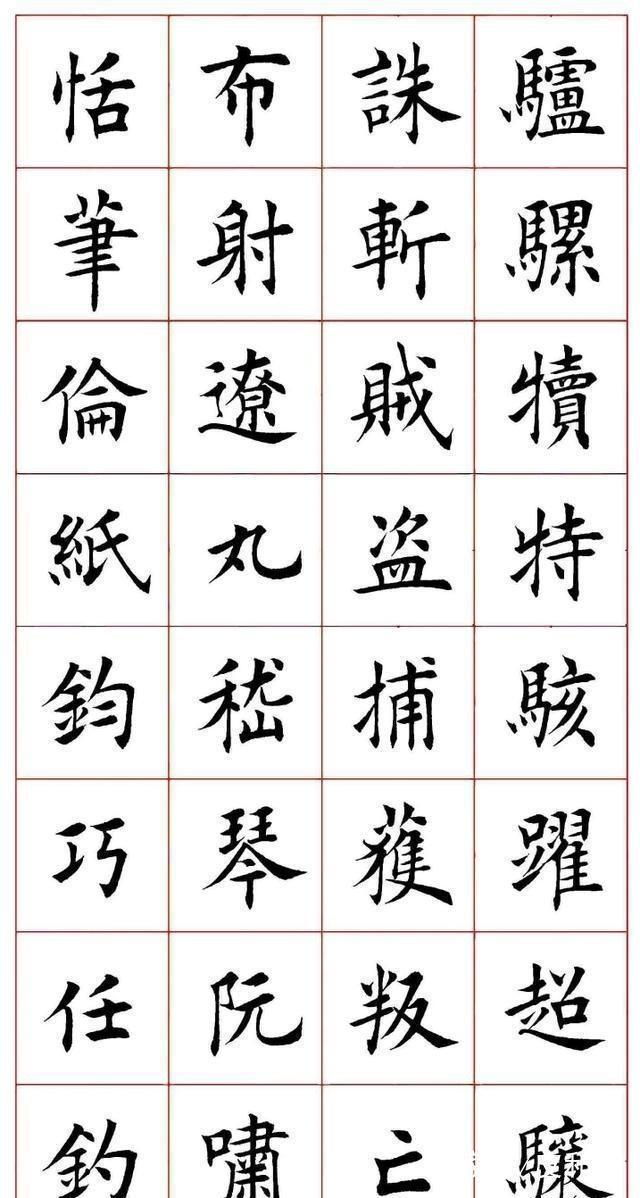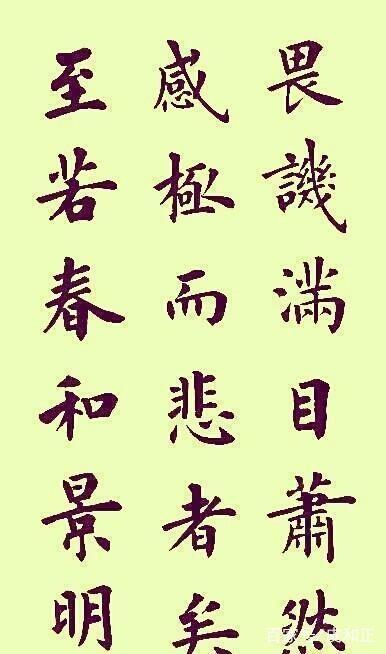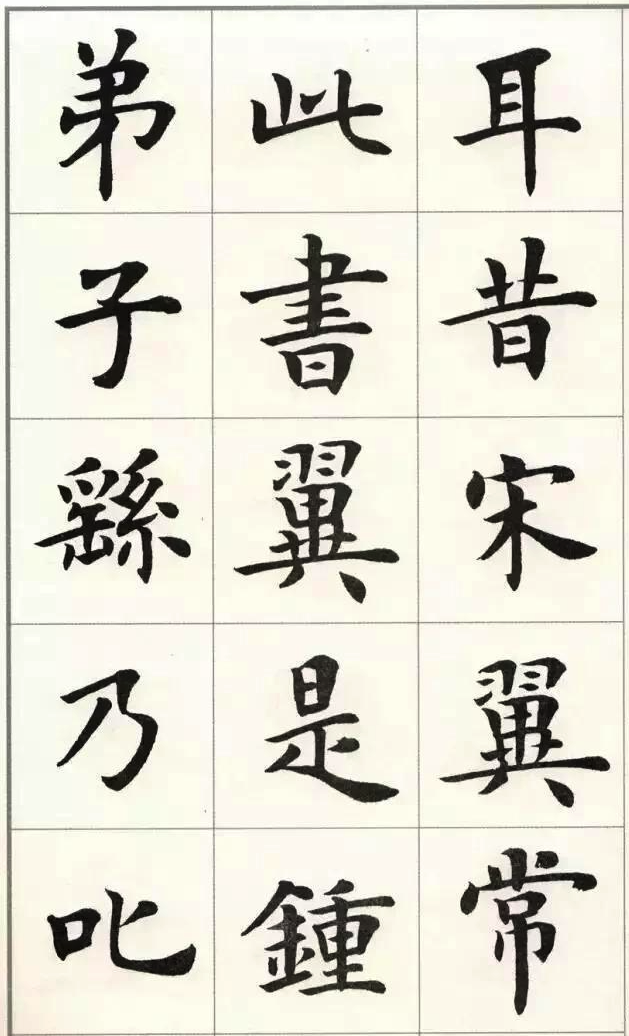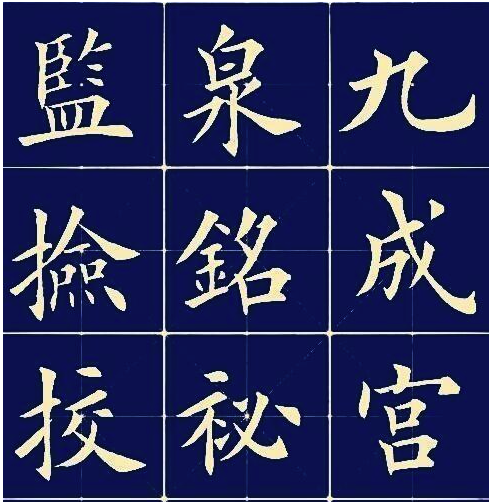
印刷体书法再做成字库是否还有意义?
无论是印刷体书法或者不是印刷体书法,能做成字库让人们做为实用性文字使用,都是一件功在当代,利在千秋的事,其意义是重大的。目前网上已出现启功、田英章、卢中南等人的书法字体。
大家知道,如果自己的字出现在互联网上,或者出现在报纸,杂志,电视等传媒上,那就是专家、学者和大众对你的书法作品的认可,说明你的书法已达到较高的水平,是一件值得自豪且有一定意义的的事情!
并不是谁的字都可以做成字库让国人作为实用性文字使用的。有的人绞尽脑汁想把自己的书法进入字库,可做字库的专家们硬是不理睬他,至于为什么,只有他们自己心里明白。
印刷体书法做成字库后,不仅体现在实用性功能上,并且还承载和传播着中国书法文化,让大众在使用汉字的同时,还可以从书法艺术之美中得到精神享受。